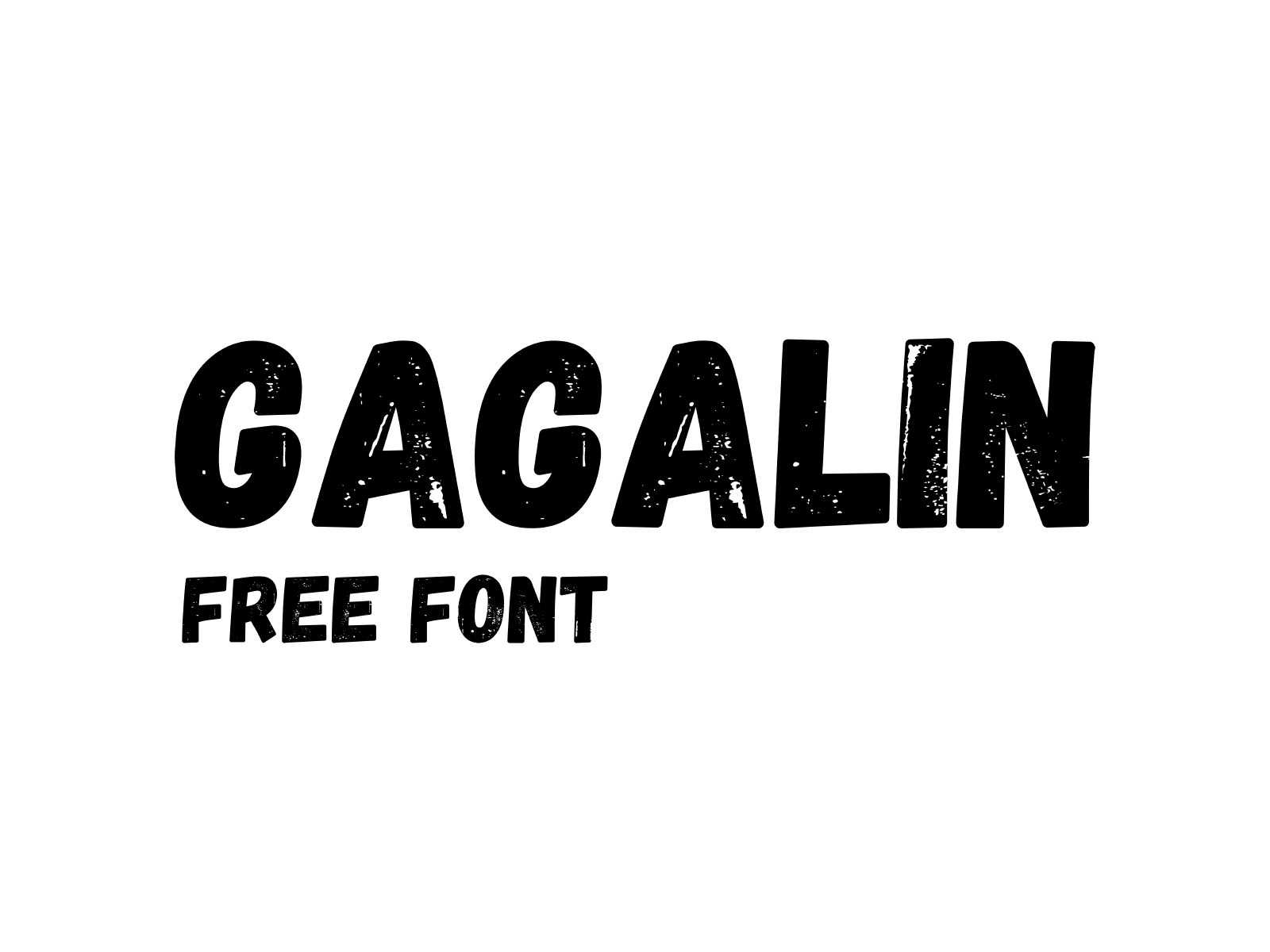
Estamos muito felizes em apresentar o Gagalin Comic Font, um recurso gráfico fantástico para criadores de quadrinhos e amantes de design. Este conjunto único de letras vem em uma variedade de caracteres, incluindo letras maiúsculas, números e uma ampla gama de caracteres especiais, garantindo uma experiência de design incrível. Com uma variedade tão vasta, você pode adicionar um toque único e divertido a qualquer projeto, seja para um projeto personalizado ou comercial. Gagalin é uma excelente opção, disponível de graça para você usar pessoalmente ou comercialmente. Este font é definitivamente o item perfeito para enriquecer sua próxima criação de quadrinhos.